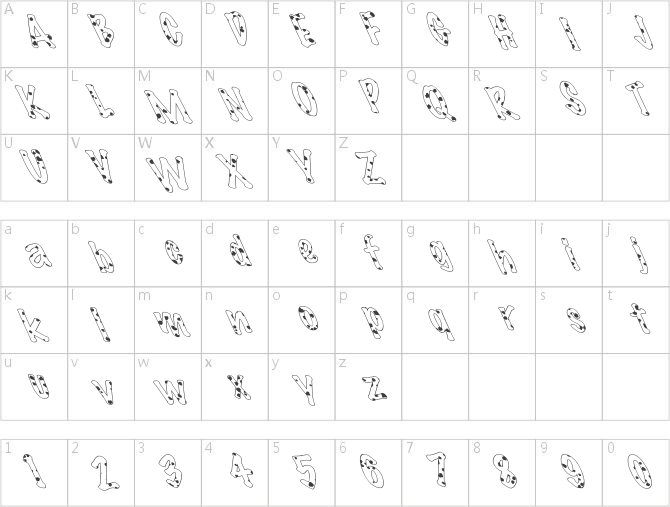
FZ HAND 14 SPOTTED LEFTY
FZ HAND 14 SPOTTED LEFTY介紹
FZ HAND 14 SPOTTED LEFTY字體字庫是一款讓人賞心悅目、百看不厭的英文字體,適合各類廣告和產品包裝設計應用,字體大小0.14MB,格式為ttf字體,上傳用戶是釜源貿易,作者/版權方為未知